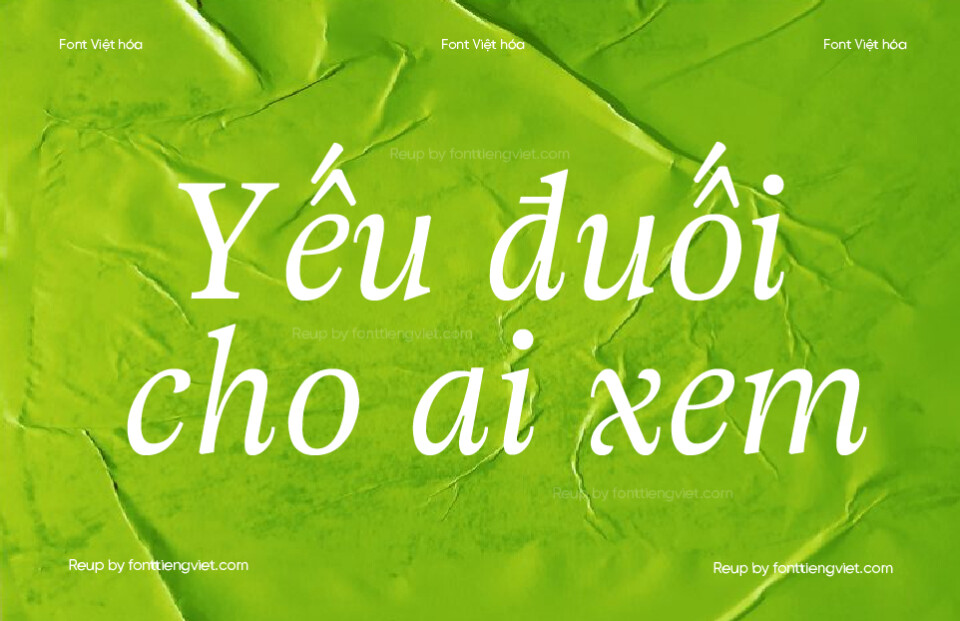
Font Việt Hóa TF Retro Gramophone – Cổ Điển & Ấn Tượng Cho Quảng Cáo
Font Việt Hóa TF Retro Gramophone – Cổ Điển & Ấn Tượng Cho Quảng Cáo là một font có chân (serif) mang đậm phong cách retro với các đường nét bo tròn mềm mại và dễ đọc. Được thiết kế với sự kết hợp giữa cổ điển và hiện đại, font này cực kỳ phù hợp cho các dự án quảng cáo cần tạo điểm nhấn và thu hút sự chú ý ngay từ cái nhìn đầu tiên.